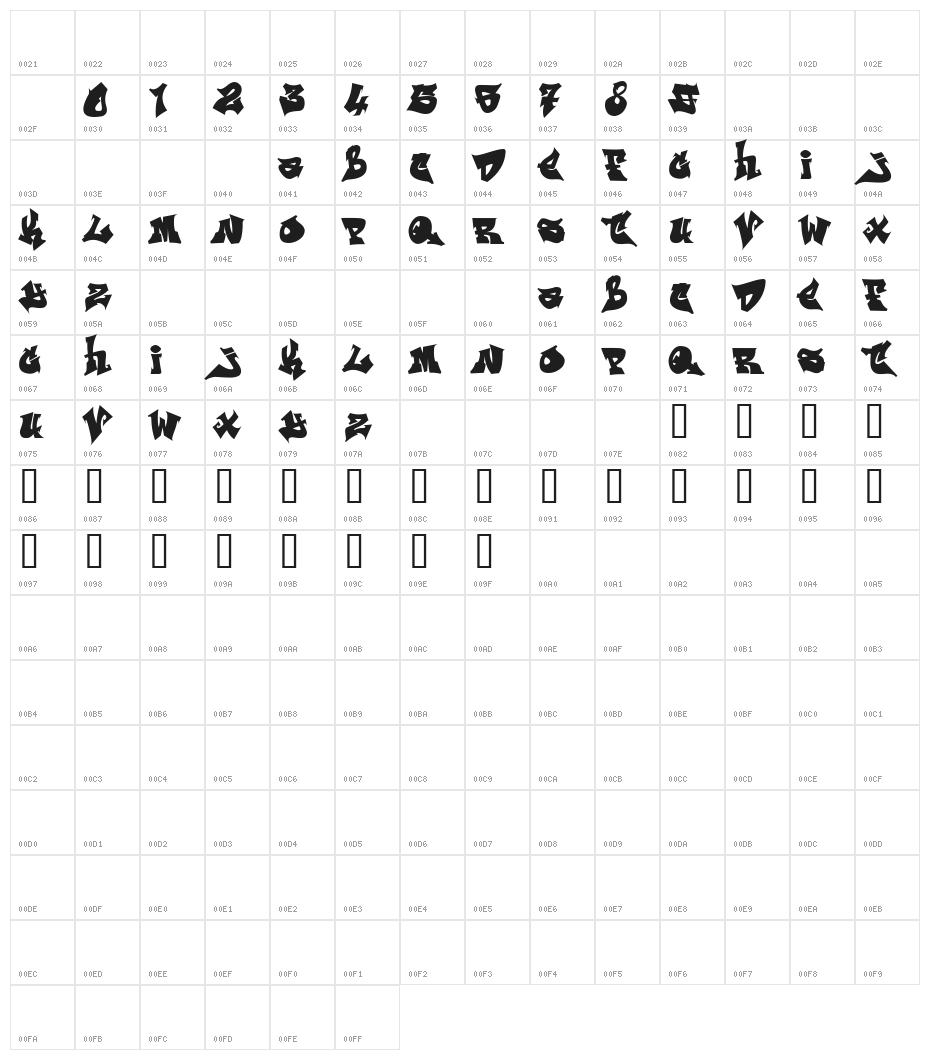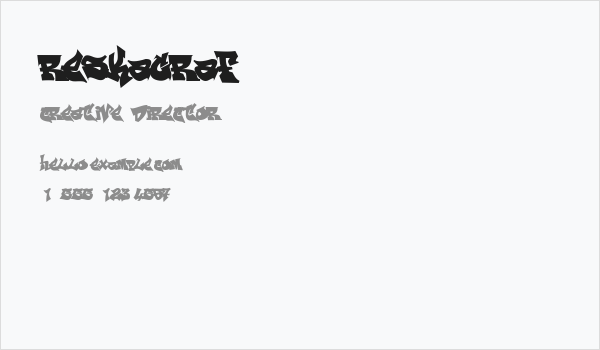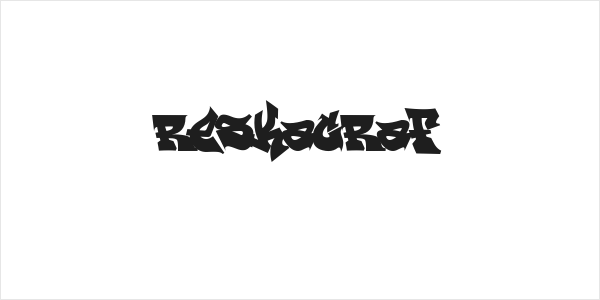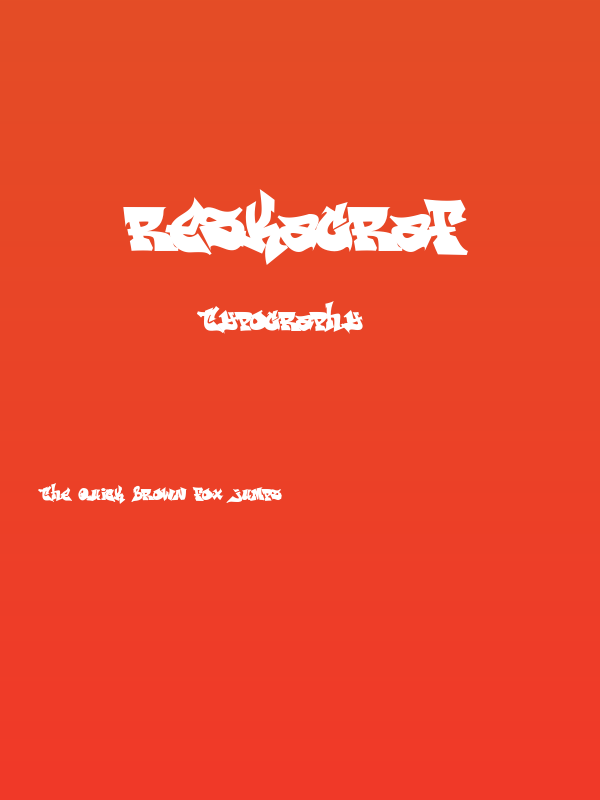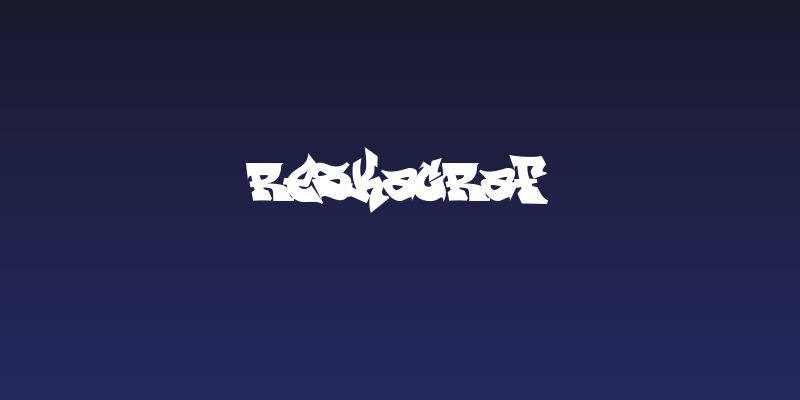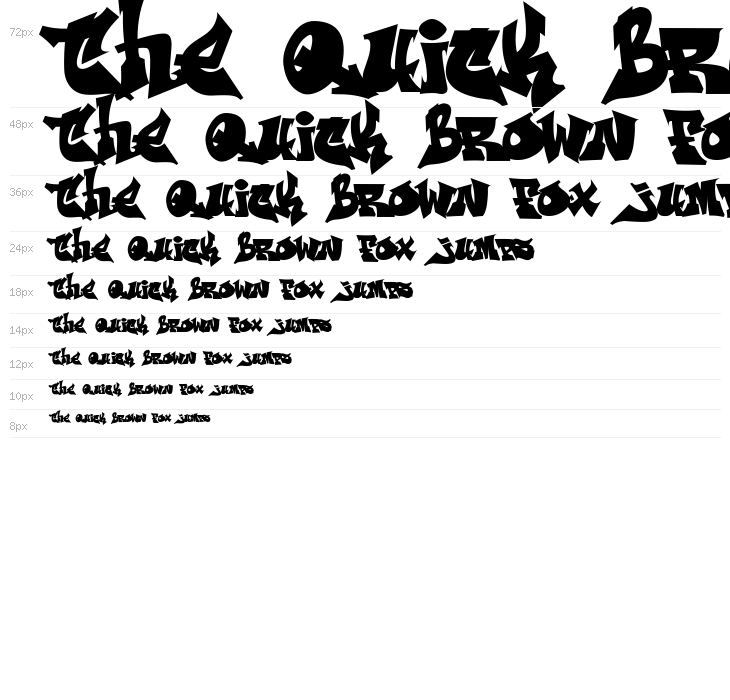
ReskaGraf Font
| Gesamtstil | Modern, Urban |
| Vorgeschlagene Projekte | Ideal for street art projects, urban-themed designs, music album covers, and edgy branding. |